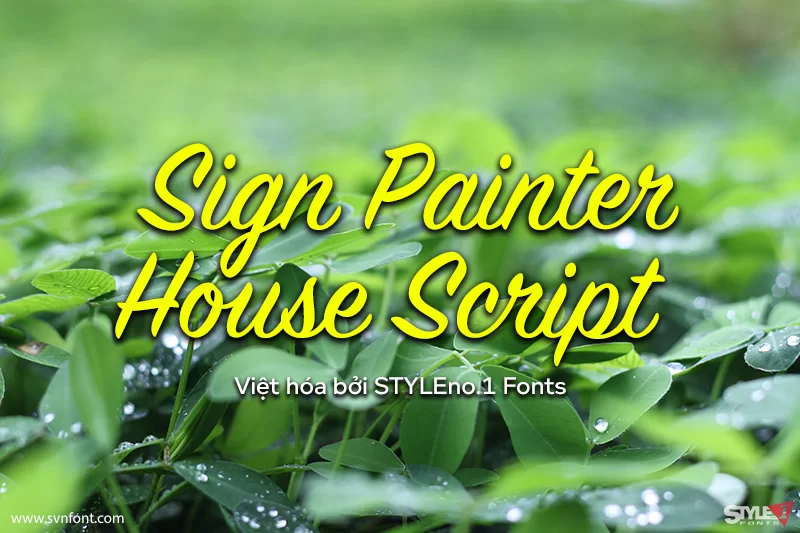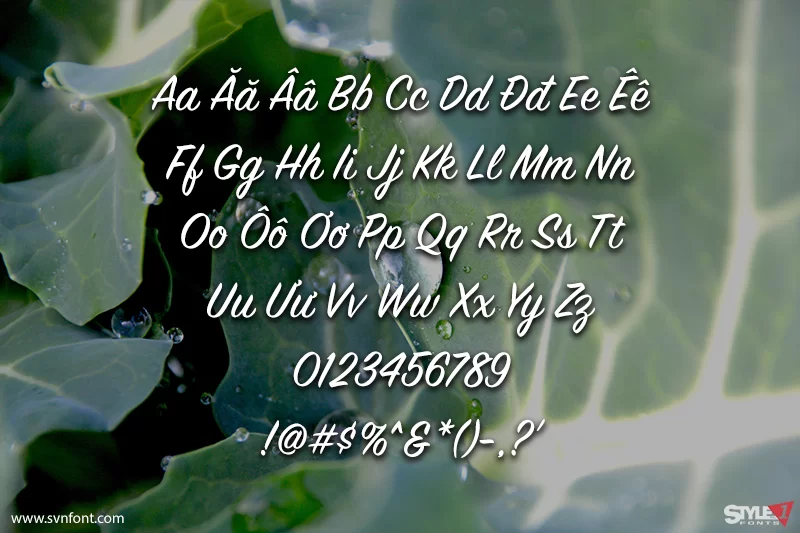
Trong nhiều thập kỷ, nghề handletterer đã trở nên không thể thiếu đối với ngành quảng cáo và thiết kế. Khi thế giới thay đổi và công nghệ mới xuất hiện, nghệ thuật viết tay đã dần dần bị quyên lãng. Tuy nhiện, hiện nay xu hướng viết tay lại có dấu hiệu phát triển mạnh mẽ. House Industries tự hào cung cấp bộ phông chữ Sign Painter House Scriptr, bộ sưu tập sáu kiểu chữ hiển thị vượt thời gian cùng với các loại hình quảng cáo bắt mắt dưới dạng font chữ ...
Nhà thiết kế:House Industries